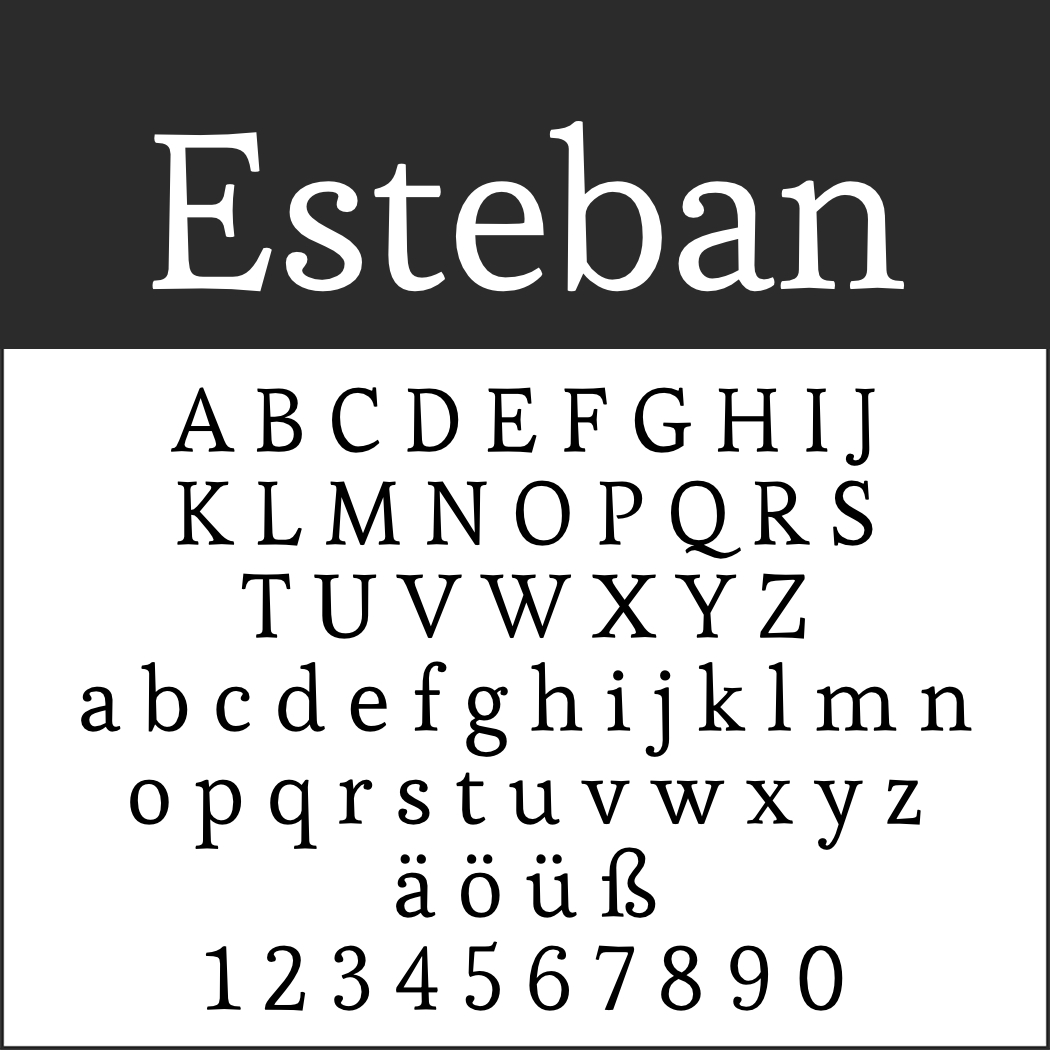
Auch ein Gutschein-Geschenk kann originell sein — mit einer guten Idee und einer ansprechenden Gestaltung. Bei letzterer spielt auch die Typographie eine große Rolle. Wenn Sie bislang noch nicht die passende Gutschein-Schriftart gefunden haben, helfen vielleicht unsere Anregungen weiter. Alle Vorschläge sind kostenlos und kommerziell nutzbar.
Gutschein-Schriftart — Gratis-Fonts zum Download
Gutschein-SchriftartBeon
Modern und ein echter Hingucker: Der französische Font empfiehlt sich besonders für Trendiges und die Ansprache einer jungen Zielgruppe.
• Besonderheit: keine Kleinbuchstaben
• Design: Bastien Sozoo (http://sozoo.fr/)
Bree Serif
Diese Schriftart erweckt den Eindruck, sorgfältig von Hand geschrieben zu sein. Noch mehr Serifenschriften finden Sie unter Serifenschriften: Gratis-Fonts und Wissenswertes.
Cotham Sans
Hervorstechend bei Cotham Sans ist das dominante G. Weitere Groteskschriften finden Sie unter Serifenlose Schriften.
Gutschein-SchriftartEngagement
Mit der schönen Pinselschrift sind Sie für alle romantischen Anlässe auf der sicheren Seite. Mehr Fonts in diesem Stil bekommen Sie unter 10 kostenlose Brush Fonts.
• Design: Astigmatic One Eye Typographic Institute
Gutschein-SchriftartEsteban
Esteban sieht nicht nur schick aus, sondern ist zudem sehr gut lesbar. Der Font eignet sich deshalb auch für den erklärenden Text auf dem Gutschein.
Helveticrap
Hemdsärmelig und improvisiert wirkt die Gutschein-Schriftart Helveticrap. Noch mehr Fonts mit Abenteuer-Flair gibt es unter Schriftart Stempel, Schriftart Schablone und Militär Schriftart.
Kalam
Kalam wirkt durch seinen Handschriftencharakter sehr persönlich. Noch mehr Auswahl in der Hinsicht bieten wir unter Schriftarten Handschrift und Zehn angesagte Handlettering-Schriften von Google.
Gutschein-SchriftartKavoon
Kavoon ist dick und fluffig. Ähnliche Schriften finden Sie auch in unseren Font-Sammlungen Dicke Schriftarten für einen starken Auftritt und Rock ’n‘ Roll Schrift bringt Schwung ins Design.
Langdon
Wenn Langdon Ihren Wunsch nach 3D und Schatten geweckt hat, sollten Sie sich auch unter 3D-Schrift für mehr Werbewirksamkeit umsehen.
Medula One
Im chilenischen Medula One vereinen sich traditionelle und moderne Elemente, nüchterner Sans-Serif-Charakter mit schwungvollen Abschlüssen.
Gutschein-SchriftartQuarry Digger
An diesem Font sieht man nicht so leicht vorbei. Mehr Aufmerksamkeitsstarkes finden Sie unter Schriften für Plakate, die alle Blicke auf sich ziehen.
Gutschein-SchriftartWolgast Two
Mit der Feder geschrieben — so muss eine Gutschein-Schriftart für Nostalgisches aussehen. Mehr in diesem Stil gibt es unter Kalligraphie-Schriftarten und Geschwungene Schriften.